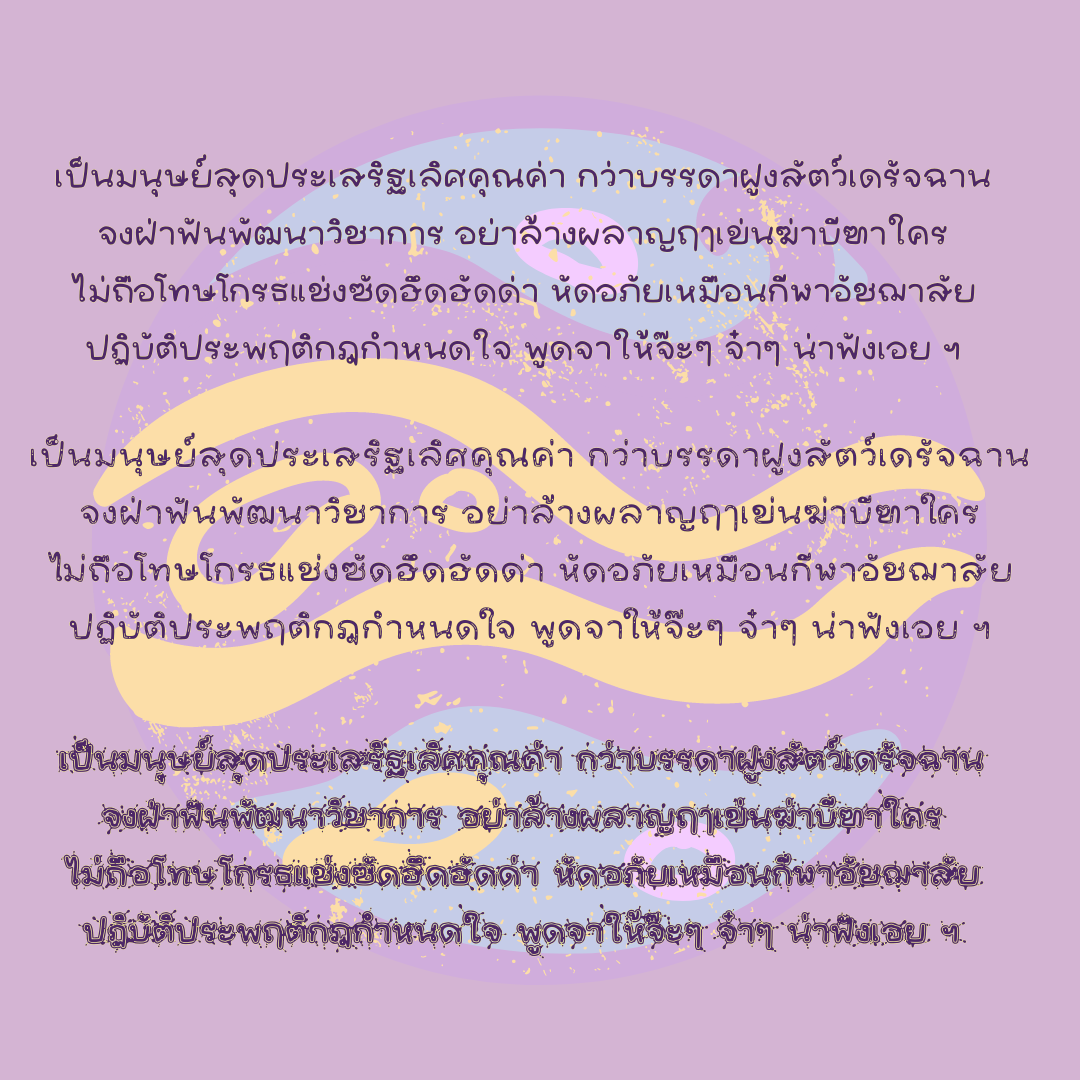
นูร่าฟอยู (Nura for you)
ฟอนต์ลายมือวาไรตี้มีด้วยกัน 3 สไตล์ เวอร์ชั่นปกติ มีน้ำหนัก บาง ปกติ หนาค่ะ เวอร์ชั่นวิ้ง เวอร์ชั่นหยดสี   นูร่าราดาเปิดให้ใช้ฟรีส่วนตัว น้ำหนักบาง วิงค์ และหยดสี นะคะ